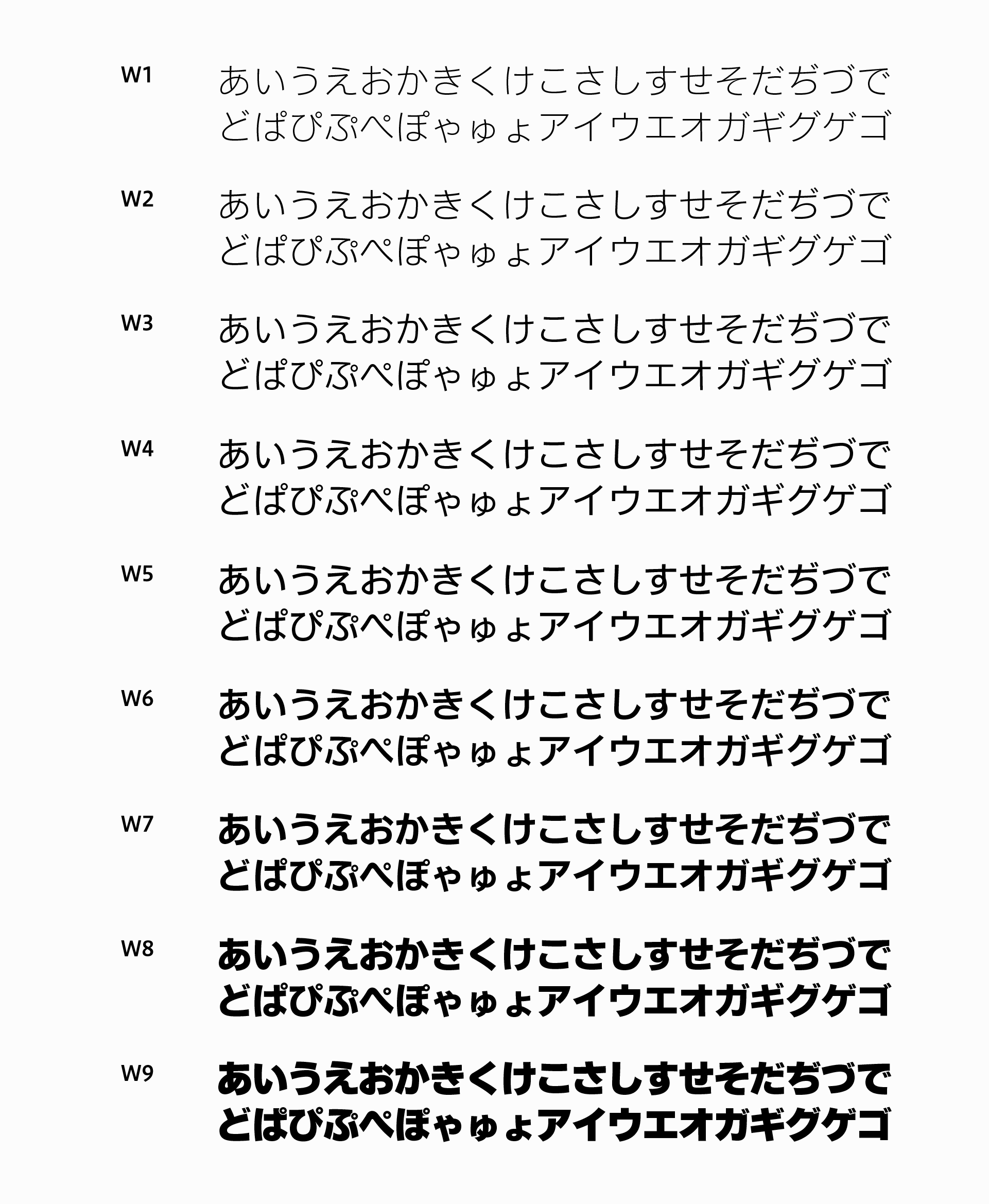
特徴
ヒラギノ角ゴAD仮名は、ひとことで言うとロゴタイプのような組み結果をもたらす整然とした仮名。字面の大きさを同一ウエイト内ではほぼ一定にしたため、横組みと縦組み、いずれの組み方向でも、文章のラインが気もちよく整った印象の文字組みになるのが特長です。ヒラギノ角ゴと組み合わせ、広告の見出しから雑誌や広報誌、テロップやコーポレートフォントなど、幅広く使いこなしていただくことができます。それでいて個々のエレメントは、ぬくもりのある手作業を感じさせる自然な曲線で構成され、特に平仮名はほとんどすべての線が緩やかな曲線で描かれているため、さらにやわらかな印象を高めています。
ヒラギノ角ゴをカバーする、W1〜W9までのウエイトバリエーションを備えています。
字形